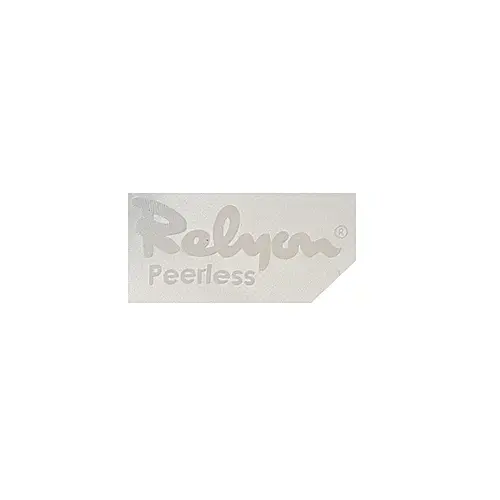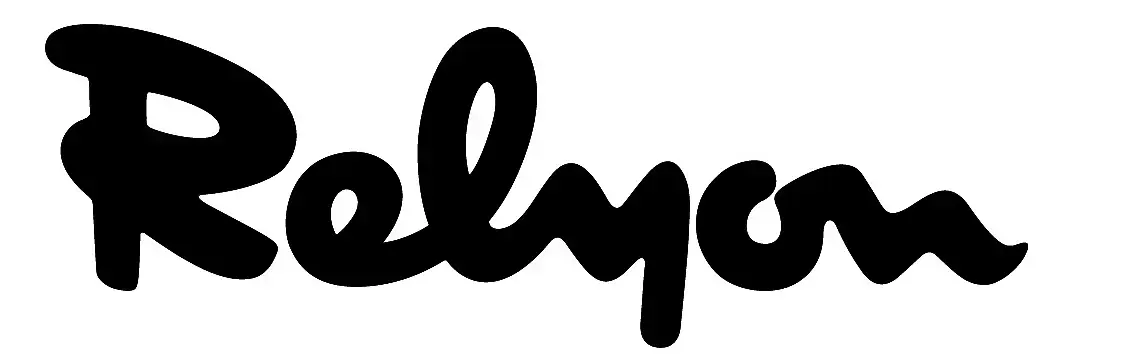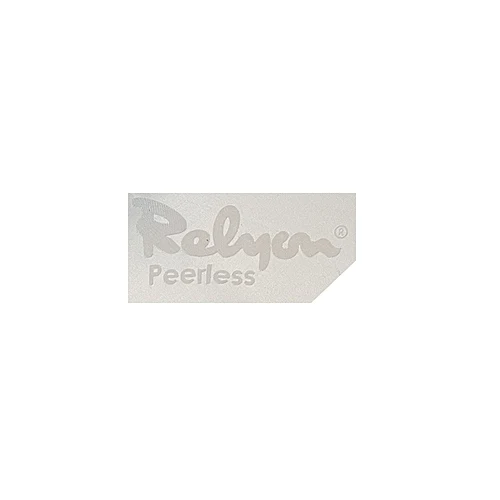
Что за шрифт?
Подскажите что за шрифт.
Есть распознаватели шрифтов, в том числе браузерные.
Ну вы хотя бы удосужились прислать нормальный логотип.
Загрузите его на сайт о котором написал ck_petya. Конкретно такого там не будет и он ищет только платные. Если нужен такой, то смотрите декоративные и прописные шрифт, например. Ищите "декоративный толстый шрифт", "декоративный прописной" и проч.
Цитата CGCat:
Ну вы хотя бы удосужились прислать нормальный логотип.
что значит нормальный?вы имели ввиду сразу готовый нужный логотип прислать?)))